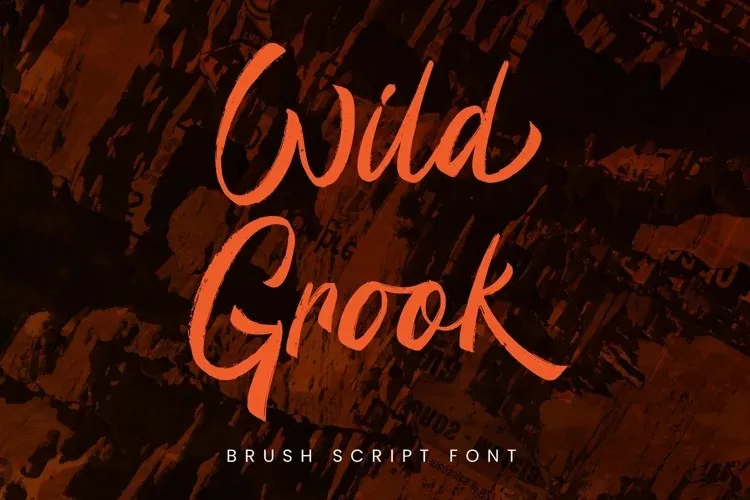
A Wild Grook Font é uma criação inovadora do Attype-Studio que oferece um estilo de letra script com um toque de ousadia e originalidade. Sua rica textura detalhada inspira-se nas tipografias urbanas, trazendo elementos únicos e vibrantes para qualquer projeto. Com suas linhas fortes e fluidas, a Wild Grook é perfeita para incorporar em designs urbanos e de rua, adicionando um toque de personalidade à sua marca ou identidade visual. Para quem busca uma fonte que combine modernidade com charme handwritten, a Wild Grook é definitivamente o item a ser testado na sua próxima peça gráfica.